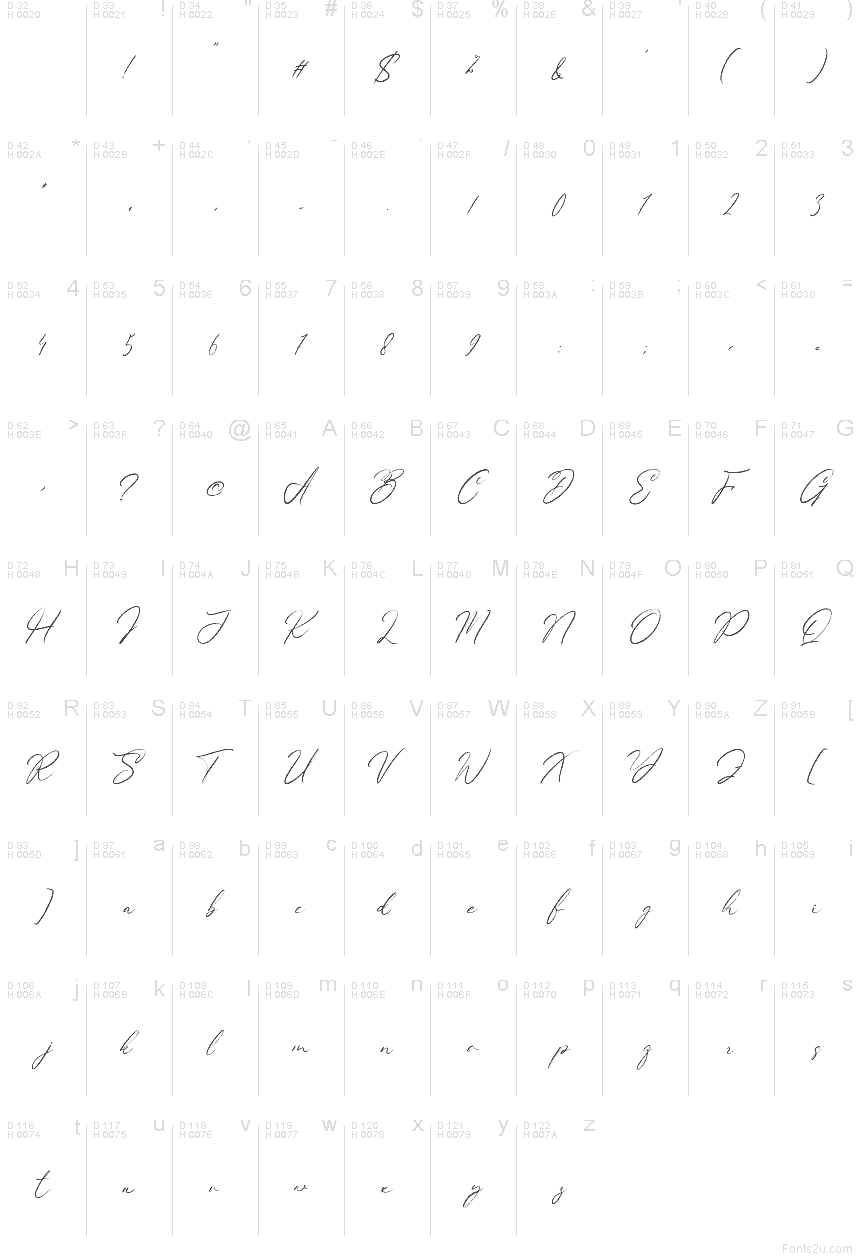
Authentipa od Pineungtype je bezplatné písmo v rukopisném stylu typu signature, definované dlouhými, vzdušnými tahy a rychlým rytmem, díky němuž písmena doslova tančí na řádku. Úzké smyčky a protáhlé počáteční tahy dodávají písmu vzhled lehce načrtnutého jména spíše než upjaté kaligrafie.
Díky tomu je přirozenou volbou pro loga, obaly, nadpisy na sociálních sítích, butikový branding a detaily pozvánek, kde osobní rukopis působí věrohodněji než formální kaligrafie. Štíhlý a plynulý pohyb písma navíc skvěle rámuje krátké fráze, názvy produktů a akcenty připomínající vodoznak, aniž by působil ztuhle nebo příliš oficiálně.